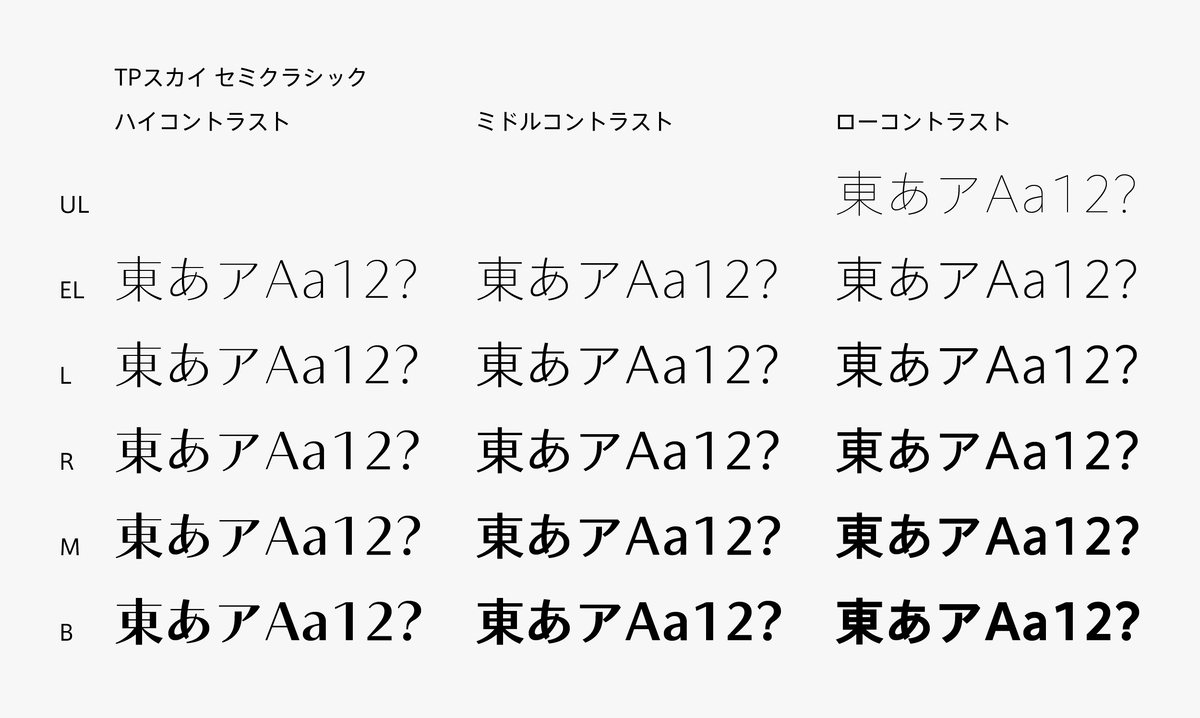
タイププロジェクトが画面表示に最適なフトコロの広さを設定してより高い汎用性の実現により、審美性と可読性のバランスを追求した「TPスカイ セミクラシック」を発表
タイププロジェクトは、TPスカイ ファミリーに和文サンセリフの可読性と審美性のバランスを極限まで高めた「TPスカイ セミクラシック」を追加したことを2024年12月2日に発表した。
「TPスカイ セミクラシック」は、シャープな印象のハイコントラスト、読みやすさと美しさの両立を目指したミドルコントラスト、手で書いたときの自然な抑揚のニュアンスを残したローコントラストの3つのコントラストで展開している。
新しさのなかに古典の面影を残し、やや引き締まった骨格と抑揚のあるストロークの相性の良さが特徴で、コントラスト軸の調整により、筆勢・遅速・強弱を表現し、文字の表情をゆたかに表している。
TPスカイ ファミリーは、ウエイト・コントラスト・字幅・フトコロ(字画内の内部空間)の4つの軸を持つ初めての日本語フォントで、簡潔で滑らかなアウトライン描画は、澄明でクリアな空気をもたらすとともに、フォントデータの軽量化に大きく貢献している。
その中でもTPスカイ セミクラシックは、もっとも審美性と可読性のバランスがとれたシリーズとなる。
タイププロジェクトの代表取締役である鈴木 功氏は、「TPスカイ セミクラシックは、弊社が長年取り組んできた和文サンセリフ体ファミリーの集大成ともいえるフォントです。可読性の高い文字骨格のあり方、画面表示に最適なアウトライン描画を追求したTPスカイ セミクラシックをさまざまなシーンでご活用いただけることを楽しみにしています」と述べている。
TPスカイ セミクラシックのハイコントラストとミドルコントラストは、EL (エクストラライト)、L (ライト)、R (レギュラー)、M (ミディアム)、B (ボールド)の各5ウエイト、ローコントラストには、極細ウエイトのUL(ウルトラライト)を加えた6ウエイトの全16フォントで提供。
TPスカイ ファミリーは、TPスカイ モダン 8ウエイト、TPスカイ48フォント(ウエイト×コントラスト×字幅)、TPスカイ クラシック(ウエイト×コントラスト)16フォント、TPスカイ セミクラシック(ウエイト×コントラスト)16フォントの全88フォントになった。
文字セット:9,499字 (スタンダード版)
ウエイト:
・ハイコントラスト/ミドルコントラスト:EL(エクストラライト)、L(ライト)、R(レギュラー)、M(ミディアム)、B(ボールド)
・ローコントラスト: UL(ウルトラライト)、EL(エクストラライト)、L(ライト)、R(レギュラー)、M(ミディアム)、B(ボールド)